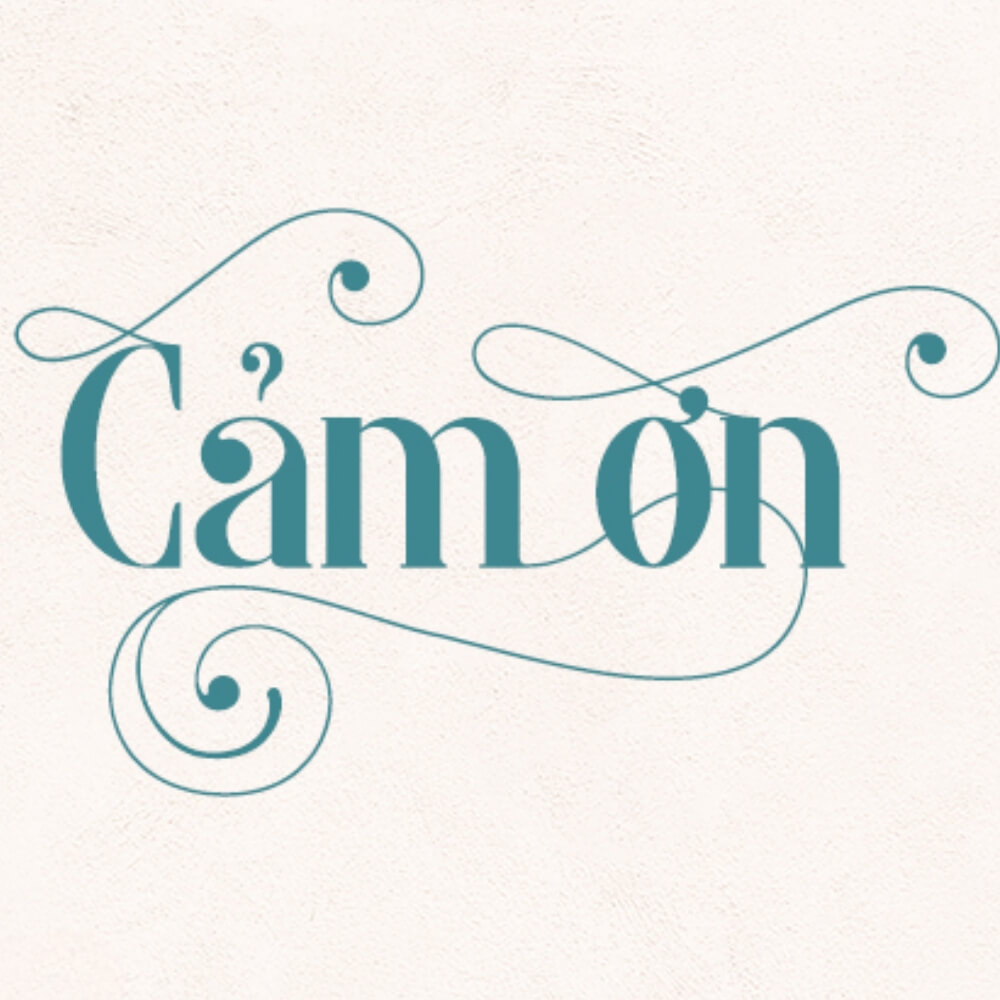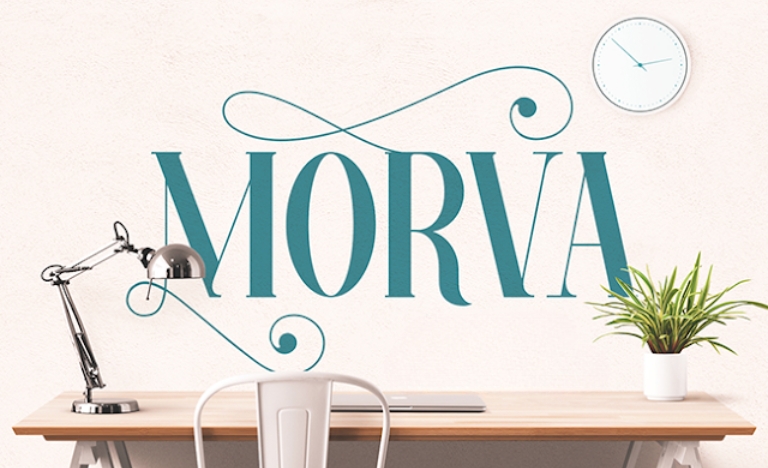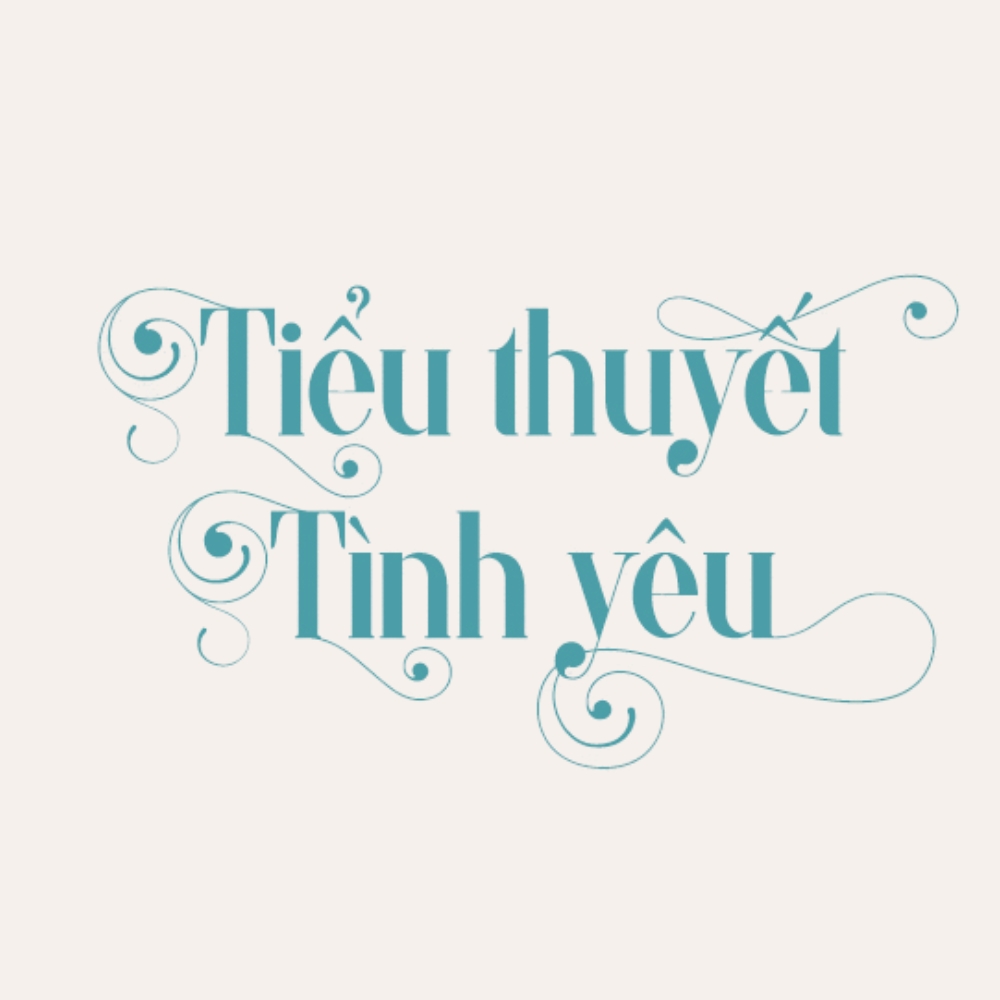
Morva là một bộ font chữ thuộc dòng Serif mang phong cách hiện đại, nổi bật với sự tương phản sắc sảo giữa các nét thanh và nét đậm. Đây là lựa chọn thường thấy trong các thiết kế đề cao tính thời thượng, quý phái và sự chỉn chu.
Sức hút từ thiết kế thanh lịch của font Việt hóa SVN Morva
Nét đặc trưng của SVN Morva nằm ở cấu trúc chữ cân đối với các đường chân dứt khoát, tạo nên vẻ ngoài vững chãi nhưng không kém phần mềm mại. Độ tương phản cao của bộ font này gợi liên tưởng đến các ấn phẩm cao cấp trong lĩnh vực thời trang và kiến trúc đương đại. Phiên bản Việt hóa bởi đội ngũ SVN giúp giải quyết triệt để các rủi ro về lỗi hiển thị dấu tiếng Việt, đảm bảo các ký tự luôn giữ được sự tinh tế và đồng nhất so với bản thiết kế gốc.
Sự ổn định của Morva còn thể hiện qua khả năng truyền tải thông điệp về sự chuyên nghiệp và tư duy thẩm mỹ có gu. Khi được ứng dụng vào tiêu đề, font chữ này tạo ra một nhịp điệu thị giác lôi cuốn, giúp người xem dễ dàng ghi nhớ thông tin. Đây là giải pháp phù hợp cho những ai đang tìm kiếm một kiểu chữ vừa mang hơi thở cổ điển, vừa mang tinh thần hiện đại để hoàn thiện các hồ sơ dự án và sản phẩm sáng tạo.
| Phân loại phong cách | Modern Serif / Fashion / Elegance |
| Đặc tính hiển thị | Độ tương phản cao, chân chữ sắc sảo |
| Mục đích phù hợp | Tiêu đề, Branding, Poster cao cấp |
Gợi ý lựa chọn: Để bản thiết kế đạt được hiệu quả thị giác ổn định, bạn nên phối hợp SVN Morva cùng một font không chân tối giản cho phần nội dung chi tiết. Sự kết hợp này giúp phần tiêu đề của bạn trở nên nổi bật mà vẫn đảm bảo tính dễ đọc cho toàn bộ bố cục.
03 Ứng dụng thực tế của SVN Morva trong không gian kiến trúc
Nhờ vẻ ngoài giàu tính thẩm mỹ và sự trang trọng, bộ font này mang lại giá trị thực tế cao khi được đưa vào các hạng mục trang trí và quảng bá công trình hiện đại:
- Bảng nhận diện cho Homestay & Boutique Hotel: Những nét chữ Morva rất ăn ý khi xuất hiện trên các biển hiệu bằng mica gương, inox hoặc khắc laser trên gỗ sơn mài. Đối với các dự án nhà lắp ghép cao cấp, font chữ này giúp không gian toát lên vẻ chuyên nghiệp và tinh tế.
- Trình bày hồ sơ năng lực dự án: Sử dụng font này cho tiêu đề các trang mục lớn trong hồ sơ giúp thể hiện tư duy thẩm mỹ và sự chỉn chu của đơn vị tư vấn, hỗ trợ khách hàng dễ dàng nhận diện phong cách chuyên nghiệp của dự án.
- Trang trí nội thất và số phòng nghệ thuật: Bạn có thể dùng font Morva để thiết kế các bảng tên phòng, biển chỉ dẫn tại khu vực sảnh chờ nhà lắp ghép hoặc văn phòng container nhằm tạo điểm nhấn thanh lịch cho không gian sống.
03 Lưu ý kỹ thuật khi sử dụng font Việt hóa SVN Morva
Để khai thác hiệu quả vẻ đẹp của dòng font Modern Serif này mà không làm rối mắt người đọc, người thiết kế nên lưu tâm một số kinh nghiệm sau:
- Kiểm soát kích thước in ấn: Do có các nét thanh rất mỏng, bạn cần đảm bảo tệp thiết kế đạt độ phân giải cao khi thực hiện in ấn khổ lớn để các đường nét sắc sảo của chữ không bị mất đi hoặc nhòe mờ.
- Hạn chế dùng cho đoạn văn bản dài: Độ tương phản cao của Morva có thể gây mỏi mắt nếu trình bày ở kích thước nhỏ với mật độ dày. Hãy dành font này cho các tiêu đề chính hoặc các câu slogan ngắn cần sự chú ý mạnh mẽ.
- Lựa chọn nền màu tương phản: Font Morva phát huy hiệu quả thị giác tốt khi đặt trên các nền màu đơn sắc như trắng, đen, vàng đồng hoặc các màu trung tính đậm để tôn vinh sự sắc nét của từng chân chữ.